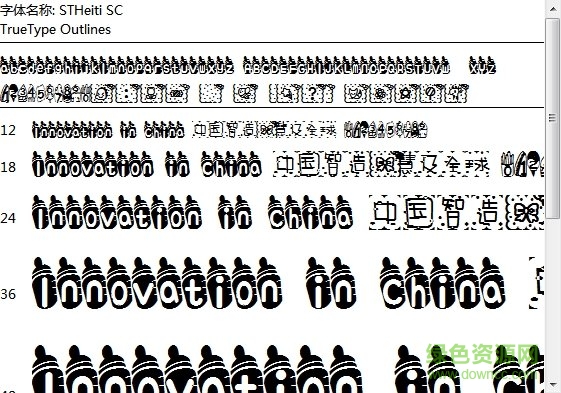
巧克力精靈字體是一款從手機(jī)字體中提取出來(lái)的個(gè)性卡通字體,字跡流暢有著多樣的點(diǎn)綴與裝飾,讓文字更加清新,如巧克力的香甜,綠色資源網(wǎng)誠(chéng)意推薦!
巧克力字體有著濃郁的巧克力香氣,給文字增加了獨(dú)特的美感,深受小女生和小孩子們的喜歡,可以廣泛運(yùn)用在藝術(shù)設(shè)計(jì)、平面設(shè)計(jì)、廣告設(shè)計(jì)等諸多領(lǐng)域當(dāng)中。